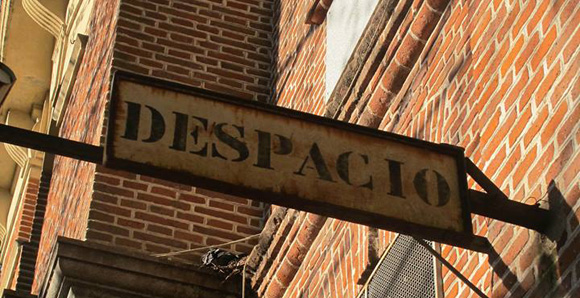
Los diseñadores Octavio Osores –ferroaficionado y “ramalero”- y Fabio Ares -especialista en tipografía histórica- se encuentran desarrollando un programa de investigación y recuperación patrimonial denominado “Tipografía Histórica Ferroviaria”. El proyecto ha sido declarado de interés académico por la Facultad de Bellas Artes de la Universidad Nacional de La Plata, institución de la que ambos son graduados (diseñadores en comunicación visual), docentes e investigadores.
Este trabajo tiene como objetivos principales investigar los usos tipográficos históricos de las compañías ferroviarias nacionales; recuperar y poner en valor la letra histórica ferroviaria como parte del patrimonio tipográfico argentino; y difundir los resultados del programa, a través de publicaciones, artículos, participación en eventos, presentaciones; y generar fuentes tipográficas digitales para distribuirlas libremente entre organizaciones beneficiarias vinculadas al ferrocarril.
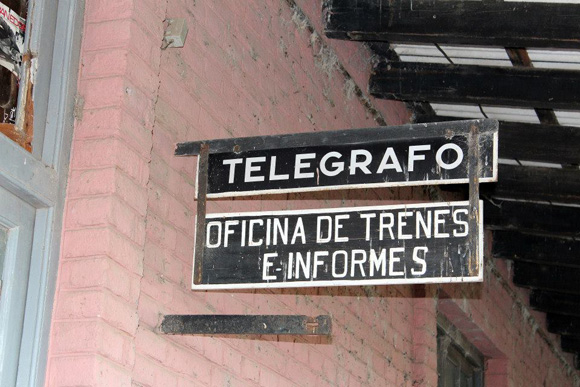
La tipografía ferroviaria es un área inexplorada en nuestro país, y un tema que estos autores consideran fundamental para el estudio y la revalorización del patrimonio tipográfico nacional. Para Fabio Ares, “los letreros ferroviarios sobreviven aún a las empresas que los importaron o fabricaron, e incluso a las estaciones que supieron identificar, a veces demolidas o abandonadas. En muchos casos, fue la única imagen que los pasajeros tuvieron de un determinado pueblo”.
Actualmente, se encuentran trabajando sobre diferentes líneas de investigación. Por un lado, se está realizando el trabajo documental y de campo tendiente al acopio de cualquier material que vincule letra y ferrocarril. Por otra parte, están desarrollando fuentes tipográficas digitales basadas en letreros del Ferrocarril Provincial de Buenos Aires, los carteles del Ferrocarril del Noreste y el Ferrocarril del Sud. Las primeras fuentes serán utilizadas por la entidad Amigos del Ferrocarril Provincial (Personería Jurídica Nº 1147, Legajo Nª 167.189, Matrícula Nª 33.224), organización sin fines de lucro que a partir de 2006 retomó la historia de la compañía ferroviaria mediante un programa para recuperar su identidad.
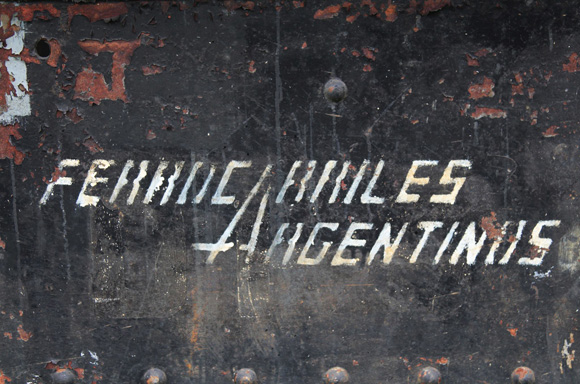
Según Octavio Osores, “la letra ubicada en los letreros de hormigón armado del ramal P1 puede describirse como de tipo display, de caja alta y estilo constructivista, de formas geométricas elementales y sin modulación del trazo. Sin dudas, su rasgo diferencial lo aportan los apéndices rectangulares que posee en ascendentes y descendentes, que ya han despertado la curiosidad de los especialistas.”